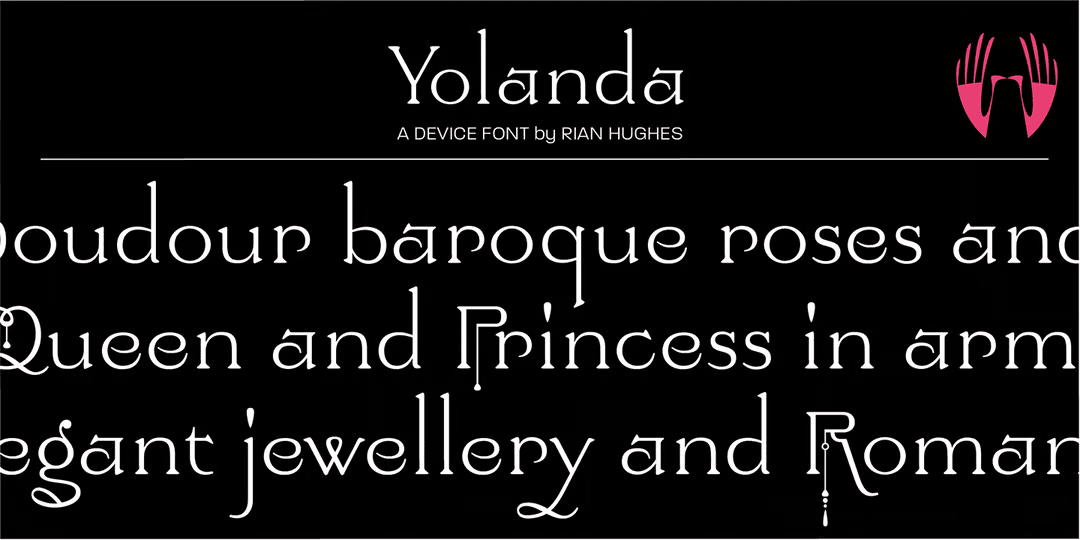
Yolanda
ヴィクトリア朝というかバロック風味というか、そんな感じのクラシカルなディスプレイ。やや変わったグリフの書体で、大文字は腰高で直線のストロークが目立ち、小文字は長いアセンダーやディセンダーが特徴。3タイプあって、Countess(伯爵夫人)はノーマル、Duchess(公爵夫人)は大文字の中央からオーナメントがぶら下がり、Princess(女王)はそのオーナメントが長く複雑になる。筆者はこのフォントをかなり昔に Mac PS フォーマットで買ってしまい(当時 OpenType は普及しておらず)、Windows ユーザーの今は使えなくなってしまった(というかデータそのものがどっか行った)。買い直さないといけないのか…。